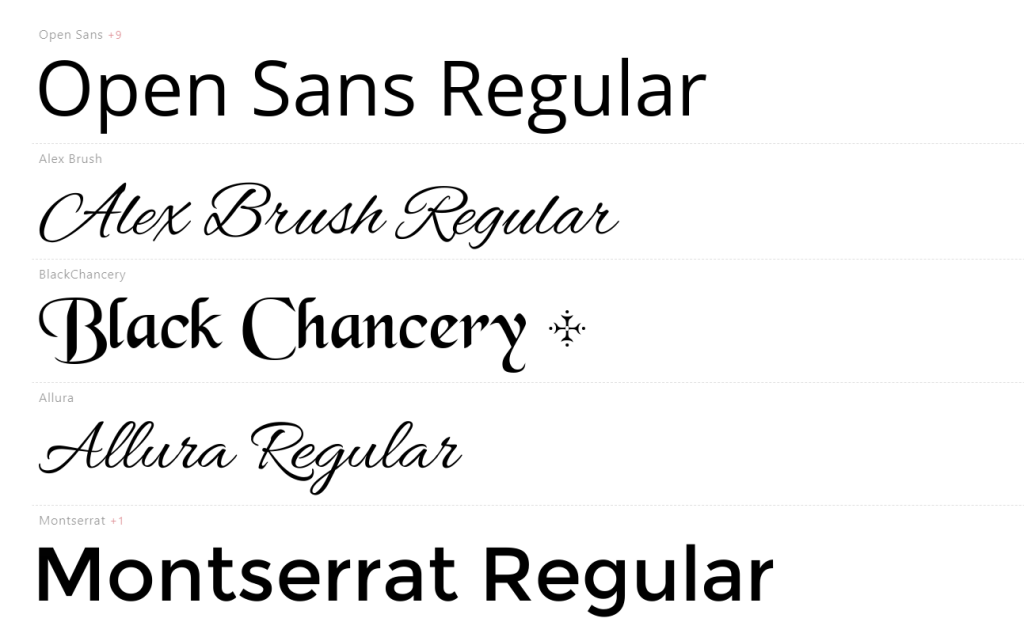
Body Text Font Free Download
Body Text Font là một lựa chọn tuyệt vời cho những ai muốn tạo ra những văn bản dài, rõ ràng và dễ đọc. Với thiết kế tối ưu hóa cho việc đọc, các font chữ TTF giúp người đọc tập trung vào nội dung mà không bị xao nhãng. Nhờ vào khả năng cải thiện tính dễ đọc, Body Text Font đã trở thành một trong những loại font chữ phổ biến nhất hiện nay.